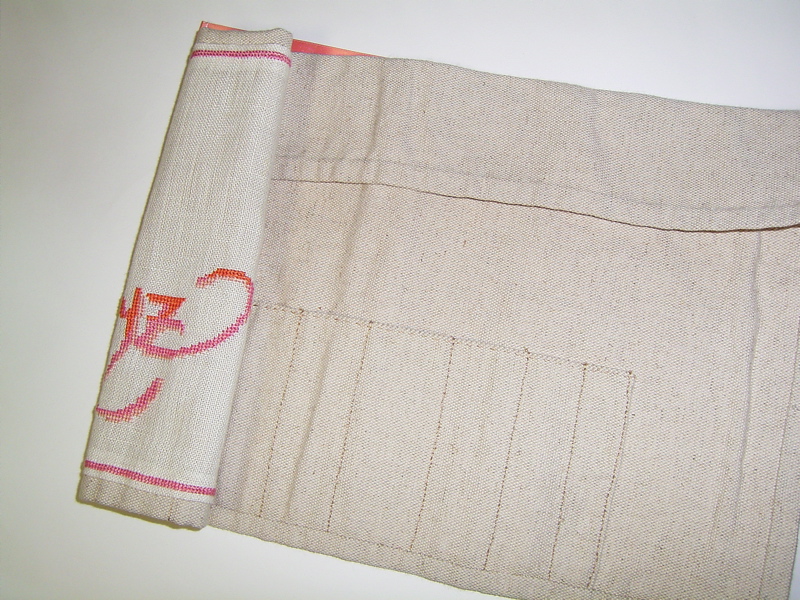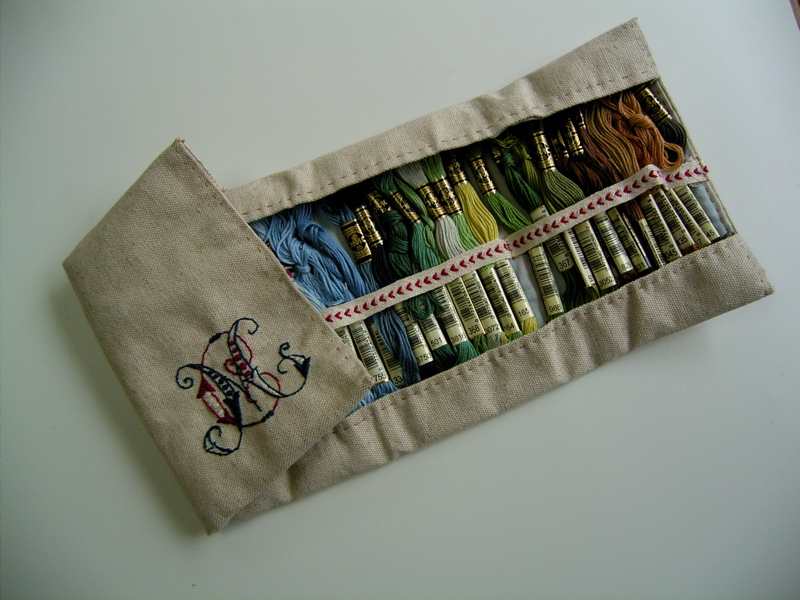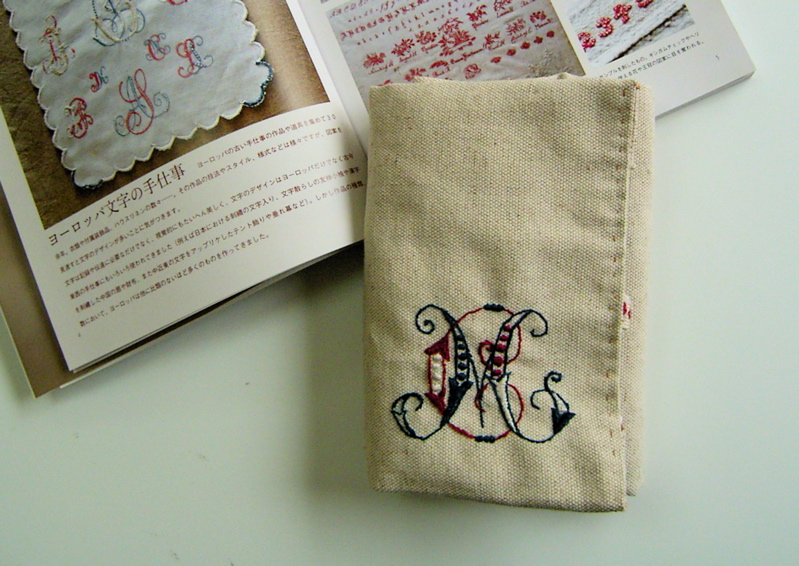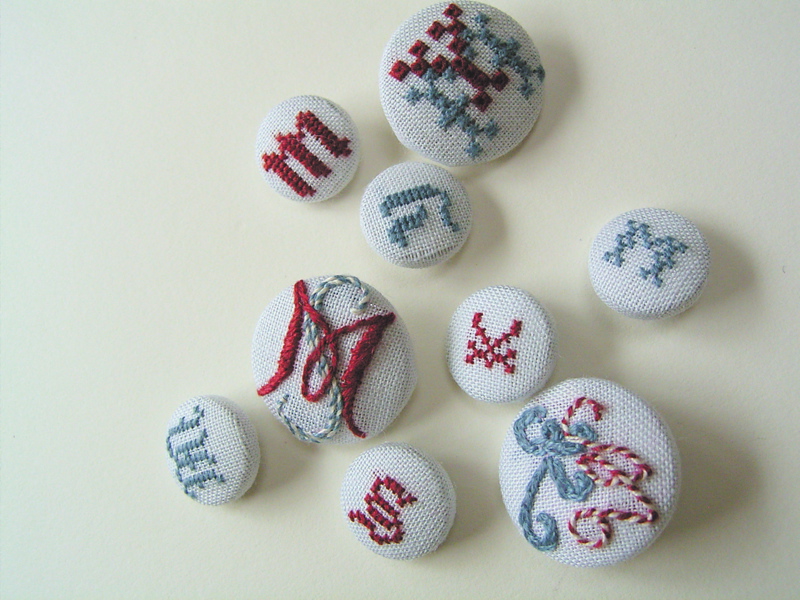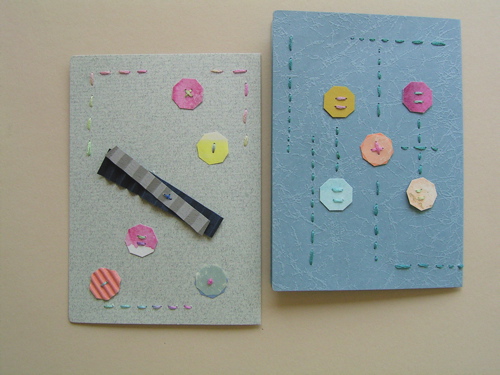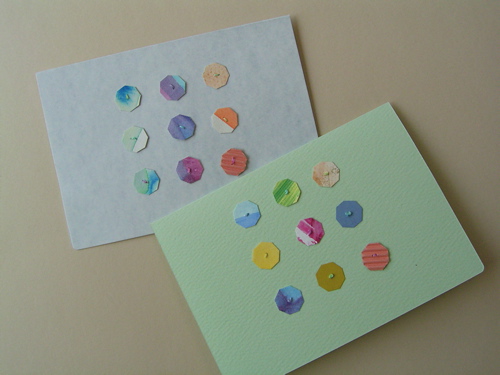
刺繍
グラデーションな糸
神奈川県のikukoさんが作り出すカードはいつもひと手間きちんとかけたもので、それなのに「私にも出来るかも」という簡単で素敵なアイデアが一杯です。
これは、もう捨ててしまおうかなというくらい小さな破片の紙を、最後の最後まで使ったデザイン。エコだわ〜・・・!
自分で色付けした紙は愛着があるから、たとえちい〜〜〜さな破片でも捨てるには忍びない。そんなときはこんな風にちっちゃく切って刺繍糸で留めてハイできあがり。
でもでも、良く見て下さい、糸の色!
毛糸ではよくありますが、刺繍糸でもあるんですね。
この裏側だけでもすごくカワイイ!
ということで私も探しに行きました。ikukoさんは「普通の刺繍糸ですよ」とおっしゃっていましたが、私が見つけたのはこんな感じの糸巻きに巻いてあるものでした。
たぶん、買っただけで満足な感じです。持っていて時折眺めては嬉しい気分になるような、そんな糸です。
その名前の通り、気分はブラボォ〜!
くるみボタンとペンケース
ついに完成した刺繍のペンケースが私のところにお嫁に来てくれました。以前ご紹介したchieさんの物を、指をくわえて眺めていたら、ちゃーんと作って下さったのでした!信じられません!
実は文字も糸の色もリボンの色も選んでの、完全オーダー品なのです!
糸の色は3色の暖色にしました。デザイン集では1行だったのを、このペンケースのサイズに合わせて2行にしてもらい、周りのステッチには、グレーも少しだけ入れてもらいました。
なんて贅沢なことでしょう。嬉しくて眺めたり開いたりして幸せ気分を満喫しています。
さて、これだけでも素晴らしいのに、なんとオマケがついていました。いーえ、オマケだなんて言わせませんっ!・・・って私が言ってるんじゃない・・
ここにいくつもあるのは他の方の分。一緒に撮らせて頂きました。私のはMとSです。
以前ご紹介した本を見て作られたそうです。
こんな素敵なものをちょいちょいと作ってしまうchieさんってどんな方?と思いますよね。
それがなんと!スーパーウーマンだったことが判明。
モノグラム刺繍
文字好きの私たちにとって、それが書いたものだろうと、彫ったものであろうと、チクチク針と糸で縫ったものであろうと、とにかく美しいものであれば、なんでも満足!何でも大好き!
ユキ・パリスさんのヨーロッパ手刺繍のモノグラムは、もうため息が出るほど美しい。この「イニシャル&モノグラムの刺繍」はいつでも手に取って眺めていたい本なのです。
イニシャル&モノグラムの刺繍―ヨーロッパ 文字の手仕事
この本には、単なる刺繍のテクニックだけでなく、ユキ・パリスさんのコレクション(アンティーク手刺繍のサンプラーやデザイン)の美しい写真がたくさん載っていて、それはそれは、幸せな気持ちになるのです。
京都には、ユキさんのコレクションが展示してある私設美術館があるそうです。関西にお住まいの方が羨ましい!
今度京都に行ったら、必ず行かなければ!
シンプルな色の組み合わせで、しかもいろいろなステッチが施されています。
色のグラデーション、クタクタっとなった糸の柔らかさ。刺繍糸って見ているだけでも嬉しくなります。
袋に突っ込んである私の刺繍糸も、こうして色順に並べたら、
きっと全く違うものに見えるだろうなぁ・・・
糸の魔法使い
ホビーショーでは毛糸の森に迷い込んで、ヘンデルとグレーテルならお菓子の家でつまみ食いというところを…mojitor-sと mojitor-hは毛糸のつまみ買い!
製本で魅惑の糸、毛糸を積極的に使用する今日この頃ではありますが…製本教室の生徒さんの中に「本当の糸の魔法使い」がいらしたのでした〜!
学ぶ時間が違うのでお会いしたことはなかったのですが、先生から頂いたDMを見るなり一目ぼれ…でした。心地良いウネウネ糸の探検物語!そんな世界に出会える予感がしたのでした。
その糸の魔法使い・川口千恵子さんの「刺しゅうwork」は昨日から始まりました。
場所は南青山…とは言え(秘境とまではいかなくとも)、青山通りからは少し中に入るのでとても静かで落ち着く場所に白いギャラリーはありました。青山は、こういうくねくね入り込んだ地帯におしゃれなお店が点在していますね…。
ご本人には初めてお会いしましたが、その刺しゅうが語るよう
に、とっても爽やかで素敵な人でした〜。
白いお部屋に掛けられた、置かれた作品たちはみんな刺しゅうでおしゃれをして私達を出迎えてくれます。その線、面、質感…これってカリ人の琴線にもきっと触れますよ〜。
川口さんは、きっとこの世界をみたときに、KT Tunstallじゃないけど、「Suddenly I See ! ! !」と思ったことでしょう…。そんな世界が見つけられたら…否、見つけたい人は、是非、足を運んでみてくださいね〜。そのパワーをもらえますよ!
刺繍本
今日は、素敵な刺繍本のご紹介です。
・・・刺繍下手な私にとって・・・ないものねだり・・・こういう本に憧れます〜!
この本は以前ご紹介した「手でつくる本」と同じ写真家さんが撮影しているので、とにかく素敵な作品がさらにカッコいいアングルでおさまっています。写真一つで作品がググッと・・・何だかギャラリーを訪れている感覚になるのです。だからこういう本は写真も重要だと実感!ですね・・・。
個人的にとてもこの方のセンスが好きです。経歴を読んでいてもネィティブアメリカンの手工芸に触れるうちに創作意欲が沸いてきた・・・という件なんかに嬉しくなってしまいます。
道具の紹介もされていますが・・・なるほどこんな便利なものがあるのか〜と感動しますね・・・。やっぱり本職さんは違うなぁ〜。職人さんみたいな道具・・・道具好きの私にはたまりません!
mojitor-tさんが憧れているアルファベットサンプラーなるものも素敵ですよね〜。
カリ人としては最終的にはアルファベットを上手くデザインして・・・かわいく?大人っぽく?品良く?なんとか刺繍という技術を用いて形にしたいなぁ・・・などとぼんやり夢をみたりなんかしています。
でも、いろんなモチーフとかは技術的には無理そうなので・・・シンプルアルファベットで落ち着くのでしょうか・・・?
ノイランドの書体なんかでカジュアルに刺繍してもいいかな・・・?
小文字で刺繍するのも可愛いかも・・・?
う〜ん、妄想は尽きませんが・・・その前にカリを練習しろっチューことですね〜。
カリを練習して、上手くなって、デザインして、刺繍したら・・・一冊のサンプル集で本にしたいです〜。